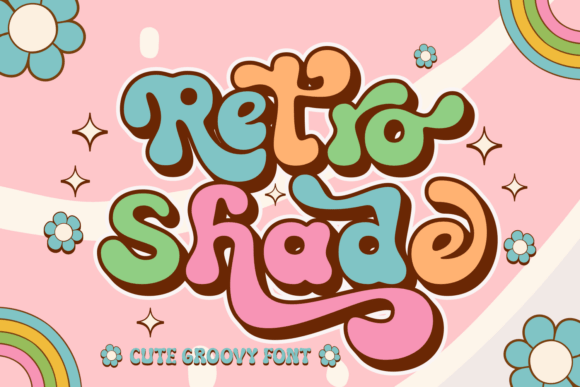
Retro Shade
Retro Shade – A Fonte que Transforma Cada Projeto em Uma Viagem no Tempo
Se você está em busca de uma tipografia que combine nostalgia retro com versatilidade moderna, Retro Shade é a escolha perfeita. Criada para trazer o charme dos anos 70‑80 ao design contemporâneo, essa fonte se destaca em branding, embalagens, peças editoriais e muito mais.
- Design limpo e arredondado – As formas suaves garantem legibilidade em tamanhos pequenos, ideal para cartões de felicitação e mensagens íntimas.
- Toques de swash elegantes – Pequenos floreios dão personalidade a logotipos e títulos de revistas, sem comprometer a clareza.
- Adaptabilidade total – De camisetas estilosas a capas de livros, Retro Shade se encaixa perfeitamente em qualquer meio, seja impressão ou digital.
- Impacto visual nas embalagens – O estilo ousado e as linhas bem definidas atraem o olhar do consumidor, tornando produtos mais desejáveis nas prateleiras.
- Atmosfera amorosa e sofisticada – Ideal para notas românticas, convites de casamento e designs que buscam transmitir calor e elegância.
Com Retro Shade, cada palavra ganha um toque íntimo que conta uma história. Seja para criar uma identidade visual marcante ou para dar vida a detalhes sutis, esta fonte oferece a combinação ideal de groovy vibes e profissionalismo. Experimente hoje e deixe sua marca falar mais alto com estilo retro.